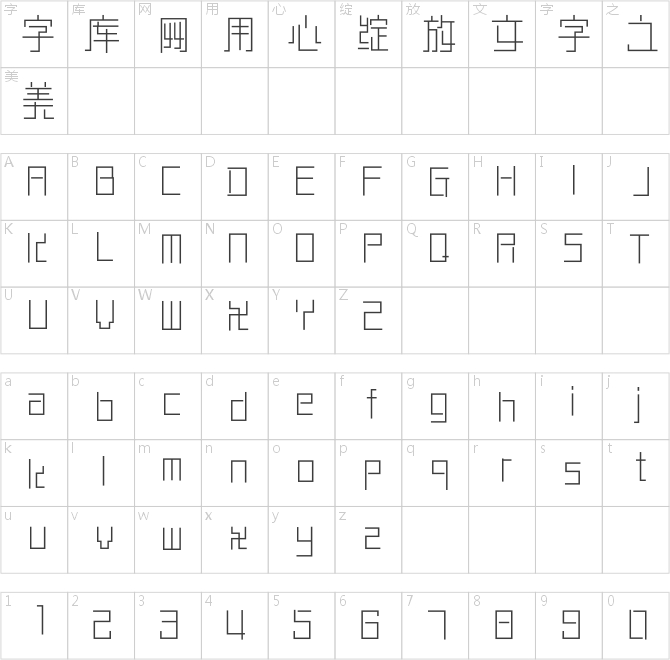
字體名稱: 漢儀清庭-55
漢儀清庭-55簡(jiǎn)
漢儀清庭-55簡(jiǎn)字體字庫(kù)是一款讓人賞心悅目、百看不厭的中文字體,適合各類廣告和產(chǎn)品包裝設(shè)計(jì)應(yīng)用,字體大小1.25MB,格式為ttf字體,上傳用戶是瀨子,作者/版權(quán)方為漢儀字庫(kù)